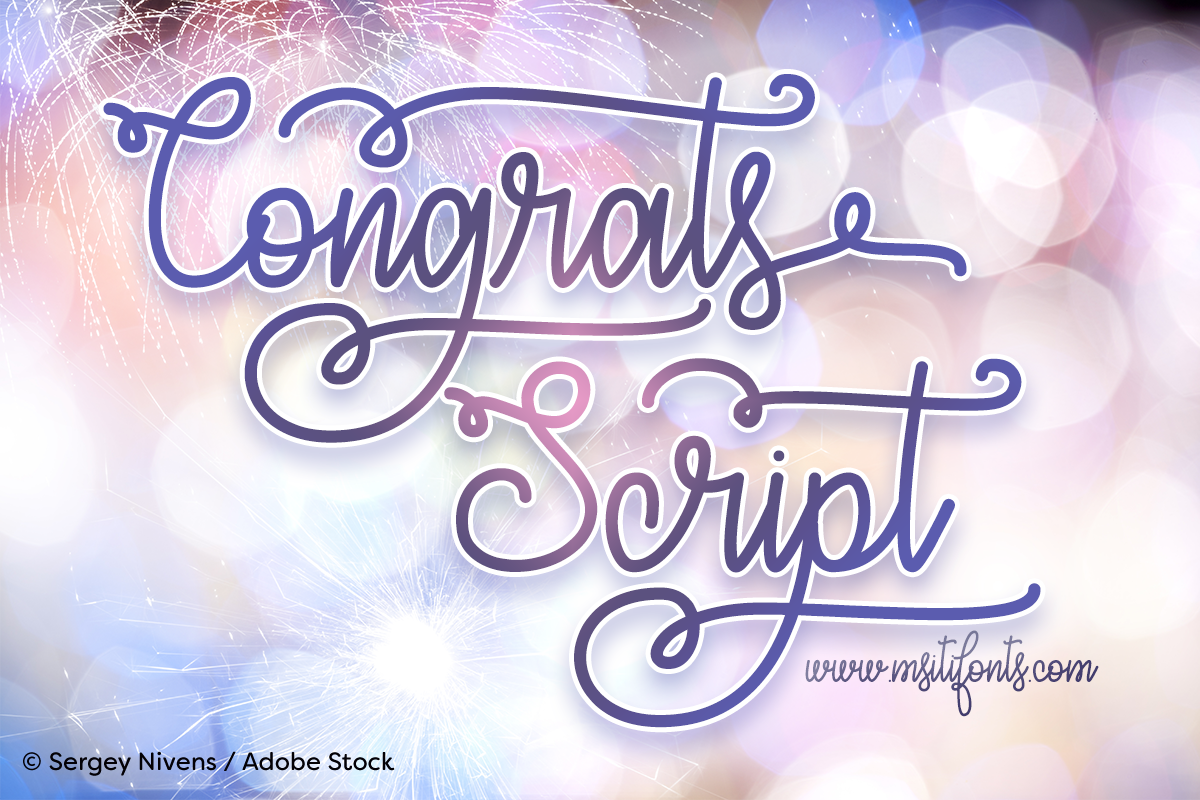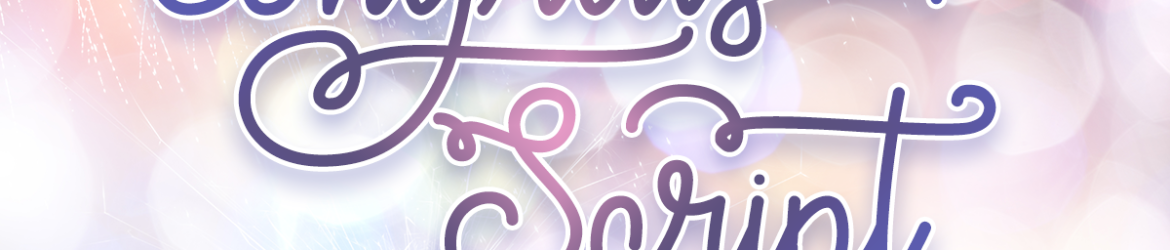
A nova solução para um projeto inicia-se com a introdução de Congrats Script Font! Esta elegante fonte tipográfica foi projetada pelo designer Misti’s Fonts e compartilhada no mundo das marcas vintage, rótulos de moda, selos e embalagens de alimentos, especialmente para rótulos de vinho. Com seu estilo script retrô que combina sofisticação com elegância, Congrats Script é perfeito para estilos minimalistas ou mais elaborados, dependendo do uso desejado. Perfecto para criar uma identidade visual única e autêntica em sua próxima campanha de marketing digital, embalagem de produto ou projeto de design gráfico. Descubra como esta fonte pode tornar seu próximo projeto ainda mais especial e memorável.